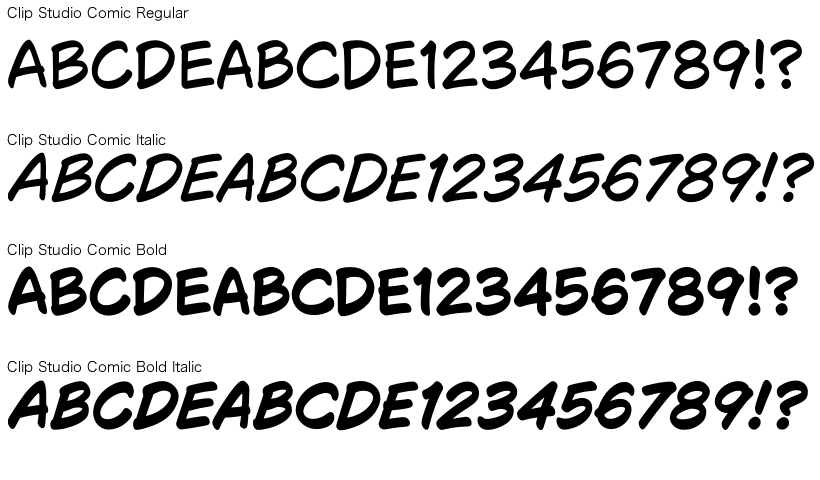
【CLIP STUDIO PAINT専用フォント】
イラスト・マンガ・Webtoon・アニメーション制作のアプリ「CLIP STUDIO PAINT」の専用欧文フォント『Clip Studio Comic』をイワタとセルシスで共同開発!
まるで手書き!?文字それぞれに4つの字形を収録。
入力する度にランダム表示され、まるで手書きのような組版を実現。
ネイティブユーザーからの希望が多かった、一人称の「I」に自動でセリフが付く機能を搭載。
使い方は無限大!
イワタDX版は追加絵文字やOutlineなどのバリエーションが仲間入りしてパワーアップ。
組み合わせて使うことで表現の幅がさらに広がります。
多言語に対応!
フランス語、スペイン語、ドイツ語、イタリア語などラテンアルファベット圏の多くの言語表記をカバー。